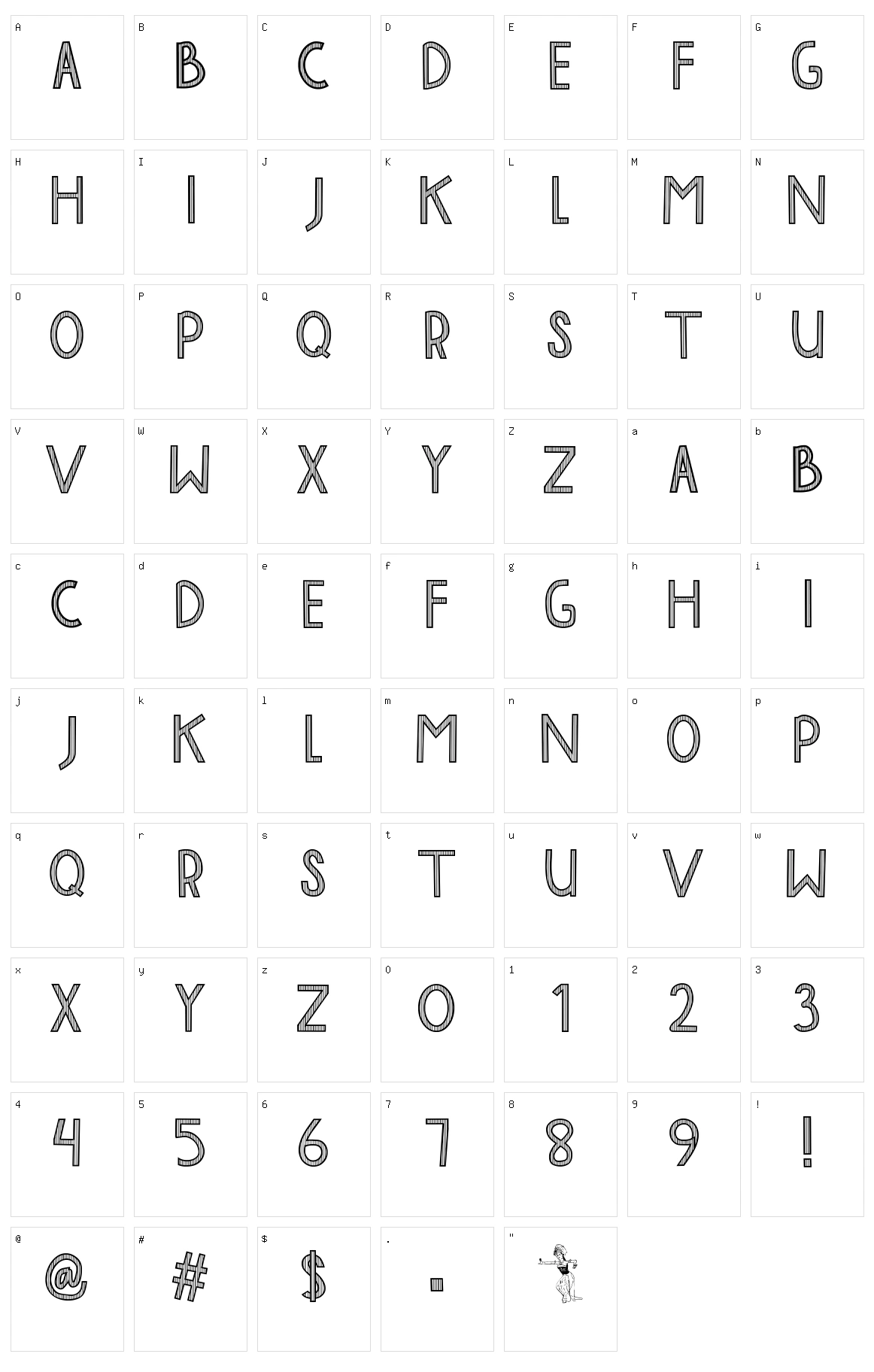
ini adalah font propaganda, walau hanya sekedar font namun ditanami
rasa amarah dan sedih jika alam di rusak hanya untuk
pembangunan yang nyatanya hanya menguntungkan pihak penguasa
tanpa mementingkan dampak yang nantinya akan di timbulkan alam !!
sebarkan font ini dan pakai dalam perlawanan melawan pihak yang hanya mementikan uang
tanpa menyadari dampak setelahnya !!
jika bukan kita anak-anak pertiwi siapa lagi !!
" jika pohon terakhir telah di tebang, tetes terakhir telah tercemar,
dan ikan terakhir telah ditangkap. barulah manusia sadar, bahwa UANG tak ada artinya "